#77 tipografia pelo mundo: Japão
como é e como atua a tipografia em um país que não usa o alfabeto latino? eu fui atrás so you don't have to :) | tempo de leitura: 6 minutos
✍️ O sistema de escrita japonês
De acordo com um artigo sobre o sistema de escrita japonês da pesquisadora francesa Émilie Rigaud, a escrita japonesa é composta por quatro tipos de caracteres: kanji, hiragana, katakana e, por vezes, o alfabeto latino pode ser incorporado.
Os sinogramas ou kanji foram “importados” da China para corresponder ao idioma japonês, por volta do século VI, e foram evoluindo de uma forma própria dentro do Japão. Esses caracteres designam o conceito da palavra, o significado. Os hiraganas são derivados do kanji, uma espécie de versão cursiva e mais rápida dos caracteres quando escritos à mão. Eles foram desenvolvidos pelas mulheres da corte imperial que eram responsáveis por escrever livros e conectam os kanjis e indicam seu papel gramatical na frase. Os katakanas também vêm do kanji. Eles eram inicialmente fragmentos de kanji usados como abreviações e são usados para palavras criadas a partir de uma língua estrangeira. Por fim, o alfabeto latino às vezes é incorporado para escrever siglas ou o título de um livro estrangeiro, por exemplo.
O sentido de leitura também é diferente da nossa: japonês pode ser escrito na vertical ou na horizontal. Na vertical, é lido de cima pra baixo e da direita para a esquerda, e na horizontal é lido da esquerda para a direita. Normalmente livros e jornais são lidos verticalmente, as páginas da internet são lidas horizontalmente e as revistas podem misturar as duas direções.
Se você está achando que são muitos caracteres… você está certo. E você se lembra dos primórdios da tipografia? Ela foi difundida com o desenvolvimento dos tipos gráficos de metal e aperfeiçoamento da prensa tipográficas pelo Gutenberg. Basicamente alinhar letrinhas pra formar páginas e imprimir - por sorte, o alfabeto latino básico tem só 26 letras. Mas o sistema japonês... Imagina a loucura que seria compor com todos os milhares de caracteres.
Foi por isso que entre o século XIX e o XX houve uma reforma no sistema, impulsionada por uma pressão para que o Japão fosse ““moderno”” como outros países. Foi necessário reduzir o número de caracteres: antes, uma sílaba podia ser representada por diferentes hiraganas. Eles decidiram manter apenas um hiragana por sílaba, e o resto deles caiu em desuso, sendo chamados de hentaigramas.
🅰️ Uma brevíssima história da tipografia japonesa
Vou pedir licença pra citar diretamente outro artigo da Émilie Rigaud, sobre a evolução tecnológica da tipografia no Japão.
Enquanto na Europa os tipos móveis eram utilizados desde o século XV, isso não funcionou no Japão até o final do século XIX. Por muitos séculos o método mais comum era a xilogravura, que usa a madeira como matriz. Cada página de texto podia ser gravada em uma única tábua, sem a necessidade de muitas peças.
Mas com o crescimento da demanda por informação (e no século XIX, isso queria dizer jornais) os tipos móveis de metal se tornaram mais relevantes, porque podiam ser reutilizados - bastava que fossem reordenados e poderiam formar uma nova página, diferente da matriz de madeira. Assim, Motogi Shōzō, considerado o pai da tipografia no Japão, fundou a Fundição de Tipos Tsukiji em 1873, a primeira do país. Os caracteres tiveram que ser adaptados para a nova tecnologia, o que fez com que suas formas mudassem um pouco, especialmente os hiragamas, de origem cursiva.
Em 1924 surgiu a máquina de fotocomposição, ou phototypesetting. Nesse processo, os tipos são negativos (branco sobre preto) e ficam em um painel de vidro, e uma luz que incide sobre a matriz “imprime” o letreiro em papel fotossensível. A tecnologia foi se desenvolvendo ao longo dos anos e na década de 1970 começou a superar os tipos de metal.
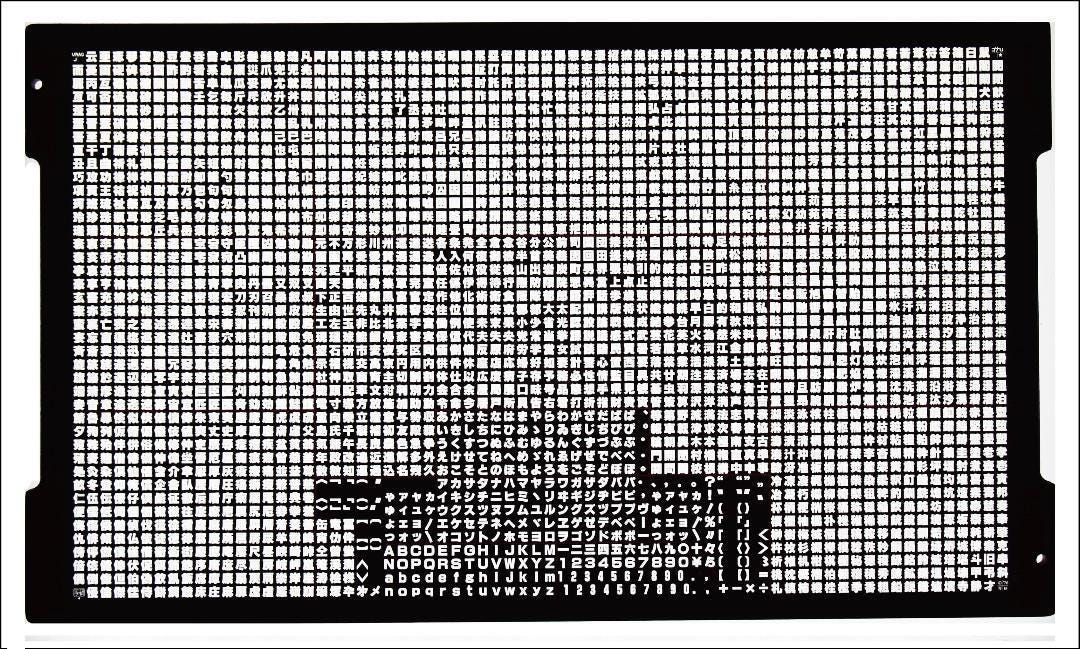
As primeiras fontes digitais surgiram na década de 1970; elas eram em bitmap e utilizadas em wâpuro (processadores de texto japoneses) ou para sinalização eletrônica de trens nas estações. Depois vieram as fontes vetoriais, algumas delas tentando atender à demanda por tipos de letra que funcionassem tanto verticalmente quanto horizontalmente.
Mas afinal, quantos caracteres uma fonte projetada para o idioma japonês precisa ter? De acordo com Akira Kobayashi, tipógrafo japonês, pelo menos sete mil. Mas esse é o mínimo - para o Google Fonts incluir uma fonte em sua biblioteca eles estimam que são necessários 23 mil. Ou seja: projetar essas fontes dá muito, muito, muito mais trabalho. Para comparação, fontes projetadas para o alfabeto latino costumam ter menos de 300 caracteres.
🔠 quais são os estilos tipográficos no Japão?
Por aqui, nós aprendemos sobre alguns estilos: com serifa, sem serifa, manuscrito… e em japonês também existem os estilos principais:
Estilo Mincho ou Dinastia Ming (明朝): Essa é a fonte serifada deles, e é o estilo mais utilizado no Japão. Dá pra notar que esse estilo reproduz os traços de um pincel.